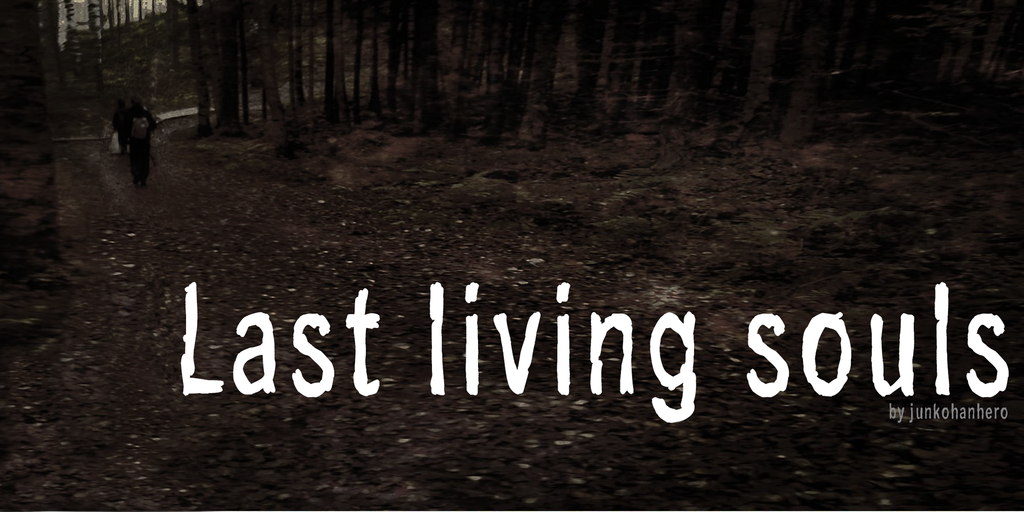
Agradeço pela sua gentileza por baixar nossa fonte ‘Last Living Souls Font Family’. Essa família de fontes escritas à mão é fruto do carinho com que criamos nossos projetos, todas para uso pessoal. Se você quiser incorporá-la em um projeto comercial, basta entrar em contato conosco no valor de 15€ ou $20 através do PayPal. Após o pagamento, envie-nos um e-mail para confirmar. Você também pode usar nosso botão de doação, bem próximo ao botão de download. Fazemos da nossa gratuidade uma maneira de incentivar outros projetistas a continuarem produzindo fontes gratuitas. Regularmente colaborarmos com vocês e valorizamos a sua compreensão.